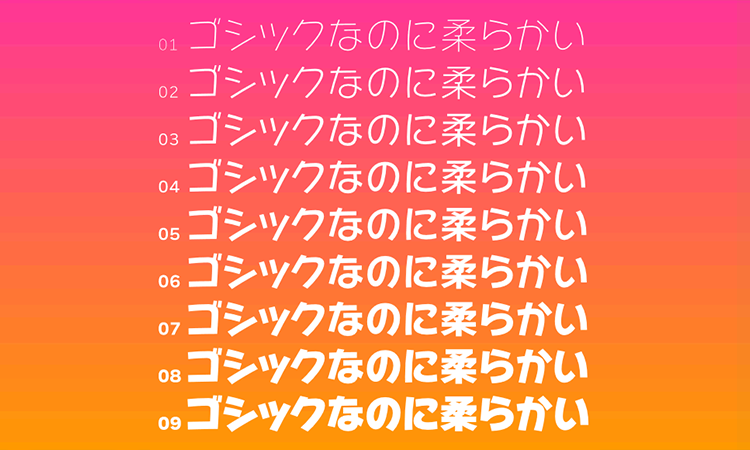
ハッピールイカ
ハッピールイカは、明るいイメージの角ゴシック体のフォントです。きっちりそした印象になりやすい角ゴシック体ですが、緩やかなカーブを組み合わせることで、読みやすさと安定感を維持しつつ、柔らかな仕上がりになっています。太さが9種類用意されており、様々な目的に使うことができます。
フォント使用例
看板やチラシ、雑誌、絵本、テレビやCM、アニメ、ゲームなど幅広い場面で使われています。使用例一覧が紹介されています。
ハッピールイカのサンプル1
ハッピールイカのサンプル2
ハッピールイカのサンプル3